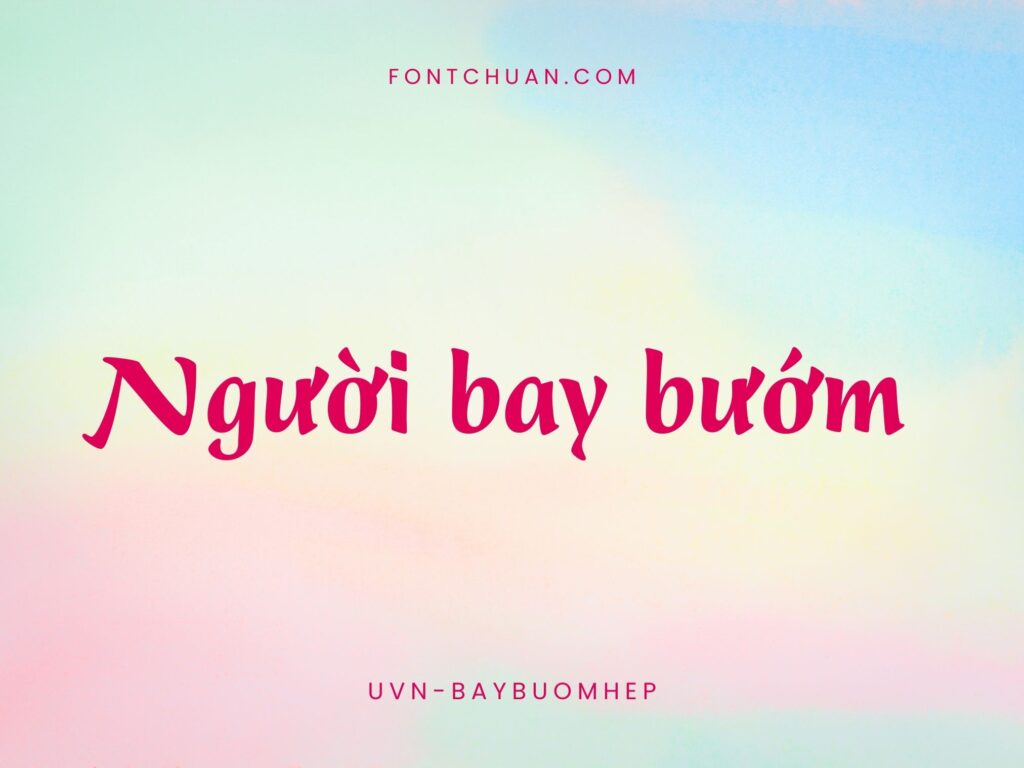
Font UVN Bay Buom Hep Việt Hóa
UVN Bay Buom Hep là một kiểu chữ script mang phong cách viết tay thanh mảnh và thanh lịch, với các đường nét uyển chuyển và hơi nghiêng, tạo cảm giác mềm mại và nghệ thuật. Font này chỉ được sưu tầm và đăng bởi thành viên của Font Chuẩn.
UVN Bay Buom Hep có cấu trúc chữ với các nét mảnh và độ nghiêng nhẹ, tạo nên sự duyên dáng và dễ đọc. Font này phù hợp cho các ứng dụng như thiết kế thiệp mời, logo, tiêu đề và các ấn phẩm in ấn yêu cầu sự tinh tế và sáng tạo. Các ngành nghề như quảng cáo, giáo dục, công nghệ và bất động sản có thể tận dụng UVN Bay Buom Hep để tạo điểm nhấn độc đáo trong thiết kế.